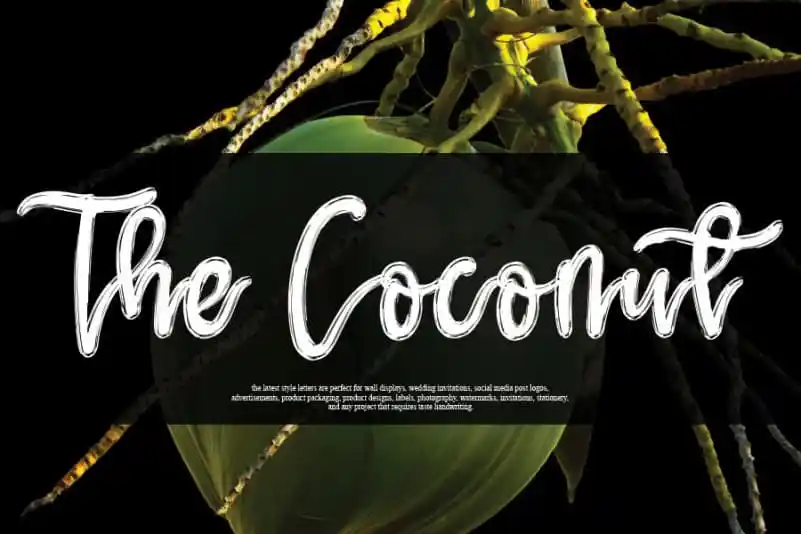
A fonte ‘The Coconut Script Font’ é uma escolha perfeita para quem busca uma fonte escrita à mão que traz classe ao mesmo tempo que transmite atualidade e frescura. Desenvolvida por andikastudio, esta fonte manuscrita mantém as influências clássicas da calligrafia enquanto também exibe um toque contemporâneo e moderno. Perfeito para os projetos que você deseja levantar ao nível mais alto, ‘The Coconut Script Font’ é a escolha perfeita para aqueles que buscam uma fonte que transmita charme e frescura sem perder sua elegância clássica. Este designer tem conseguido criar algo verdadeiramente especial em um mundo de fontes manuscritas.